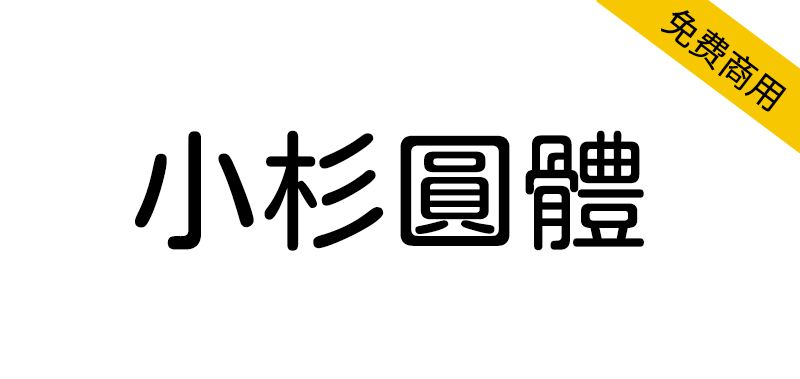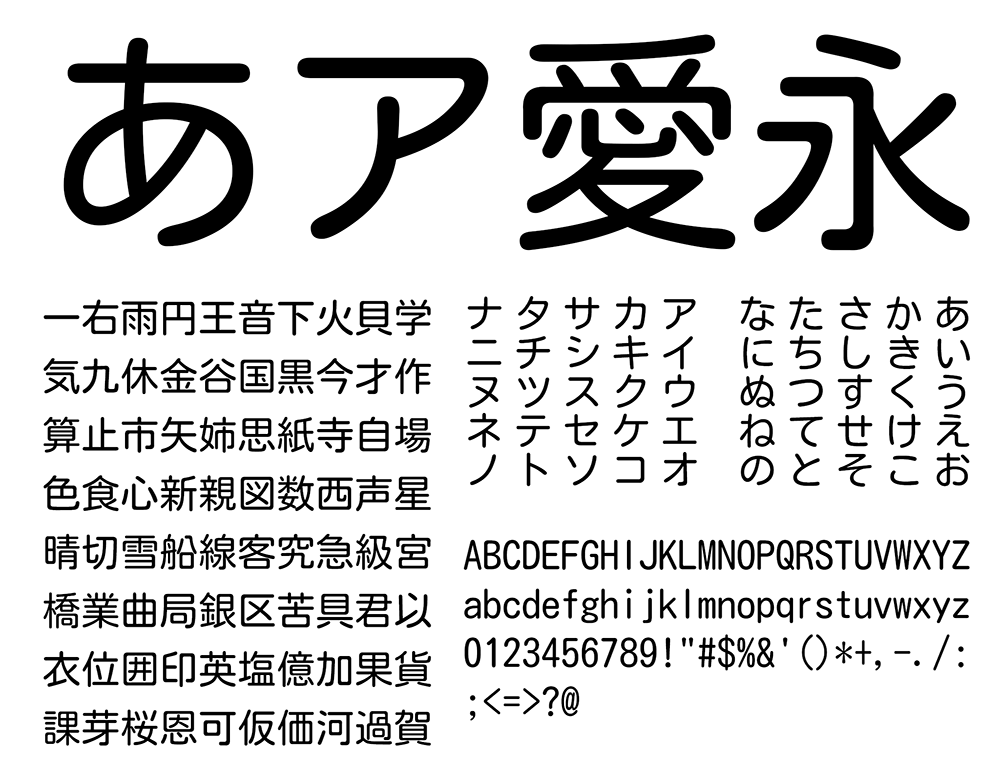
小杉圆体(英文名:Kosugi Maru)是一种哥特式圆角设计,笔画对比度低,采用等宽字体,末端为圆形。该字体最初由MOTOYA开发,并在Apache许可证下为Android平台发布,基于20世纪50年代的设计。它旨在追求美观和可读性,并唤起人们对日本雪松的联想,这些雪松有直而粗的树干和树枝。最初以“MotoyaLMaru W3 mono”的名称提供,现在以Kosugi Maru的名称提供。
Motoya字体的发展始于20世纪50年代,一直持续到今天。在此期间,Motoya字体通过支持各种排版方法,如铅字、排版字体、排版刻度盘和数字字体(位图字体/轮廓字体),改变了其产品形式。然而,在字体发展的漫长历史中,对“可读性”和“文字之美”的追求始终没有改变。
Kosugi Maru is a Gothic Rounded design, with low stroke contrast and monospaced metrics, and rounded terminals. Initially developed by MOTOYA and released for the Android platform under the Apache license, the typeface is based on a design from the 1950s. It aims for beauty and readability, and evokes the Japanese cedar trees that have straight and thick trunks and branches. Originally available as "MotoyaLMaru W3 mono", it is now available under the name Kosugi Maru.